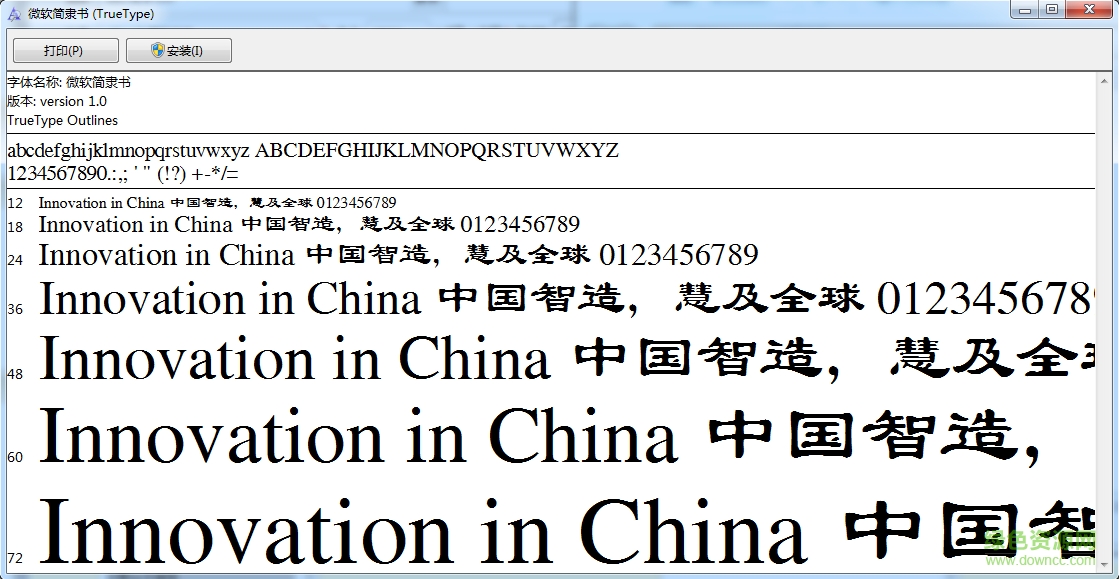
ctlishusj是什么字體?ctlishusj字體是一款簡體隸書字體,整體呈扁形,頓挫沉穩(wěn),雅俗共賞,適用于影視字幕、網(wǎng)頁設計、雜志期刊等各個領域,歡迎免費下載!
隸書字體是漢字中常見的一種莊重的字體,書寫效果略微寬扁,橫畫長而直畫短,呈長方形狀,講究"蠶頭雁尾"一波三折"隸書起源于秦朝,由程邈形理而成,在東漢時期達到頂峰,書法界有"漢隸唐楷"之稱.